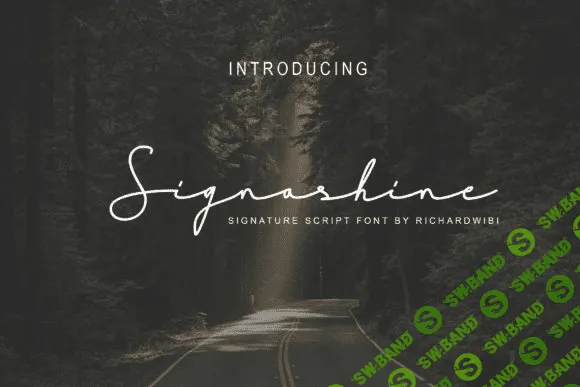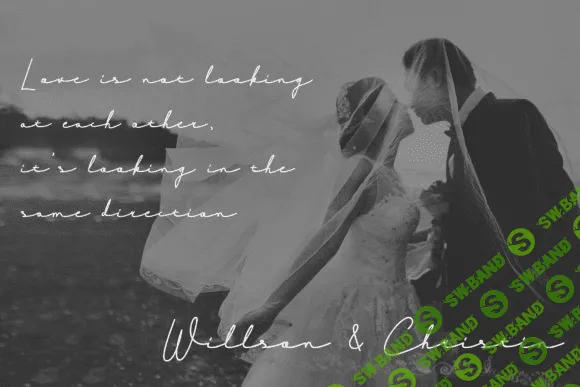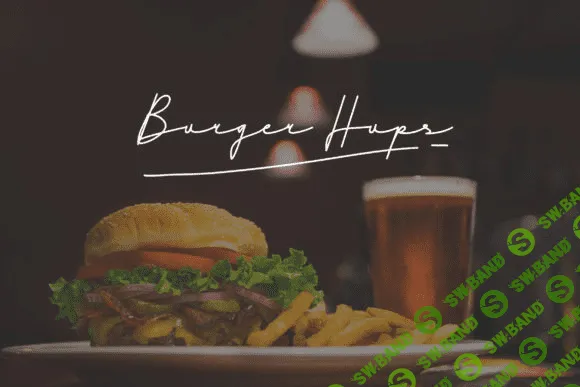
Название: Signashine Font
[creativefabrica] Signashine Font
Описание:
Signashine - это элегантный и естественный шрифт для рисования от руки. Его можно использовать для различных целей, таких как дизайн футболки, плакаты, наклейки, цитаты, обложки книг, приглашения, логотипы и многое другое.